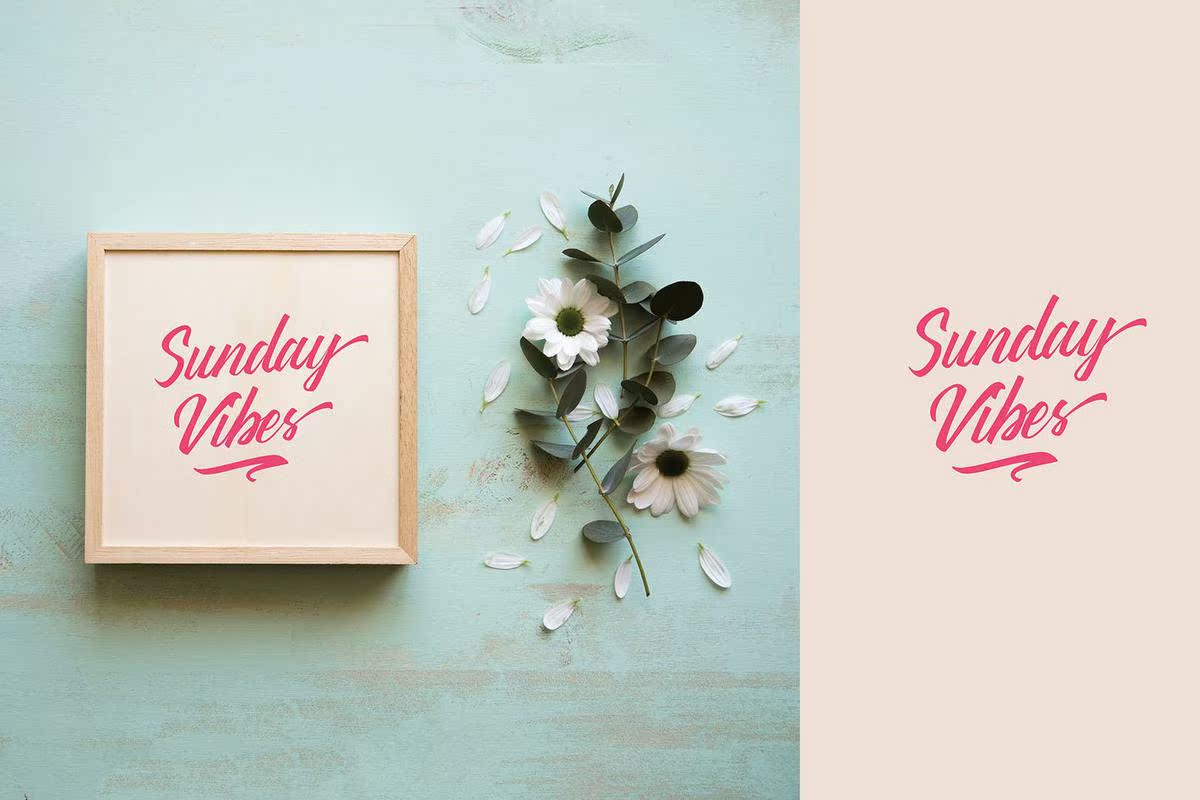
BatriyshisaboldScriptTrashTypefaced由Sotibrother创建,这款独特的字体适用于任何设计项目,如徽标和品牌、邀请函、文具、婚礼设计、社交媒体、广告、产品包装、产品设计、标签、照片、水印、,任何需要正宗手写品味的特殊物品。这款独特的字体由Sotibrother创建,适用于任何设计项目,如徽标和品牌、邀请函、文具、婚礼设计、社交媒体、广告、产品包装、产品设计、标签、摄影、水印、,需要正宗手写品味的任何东西。